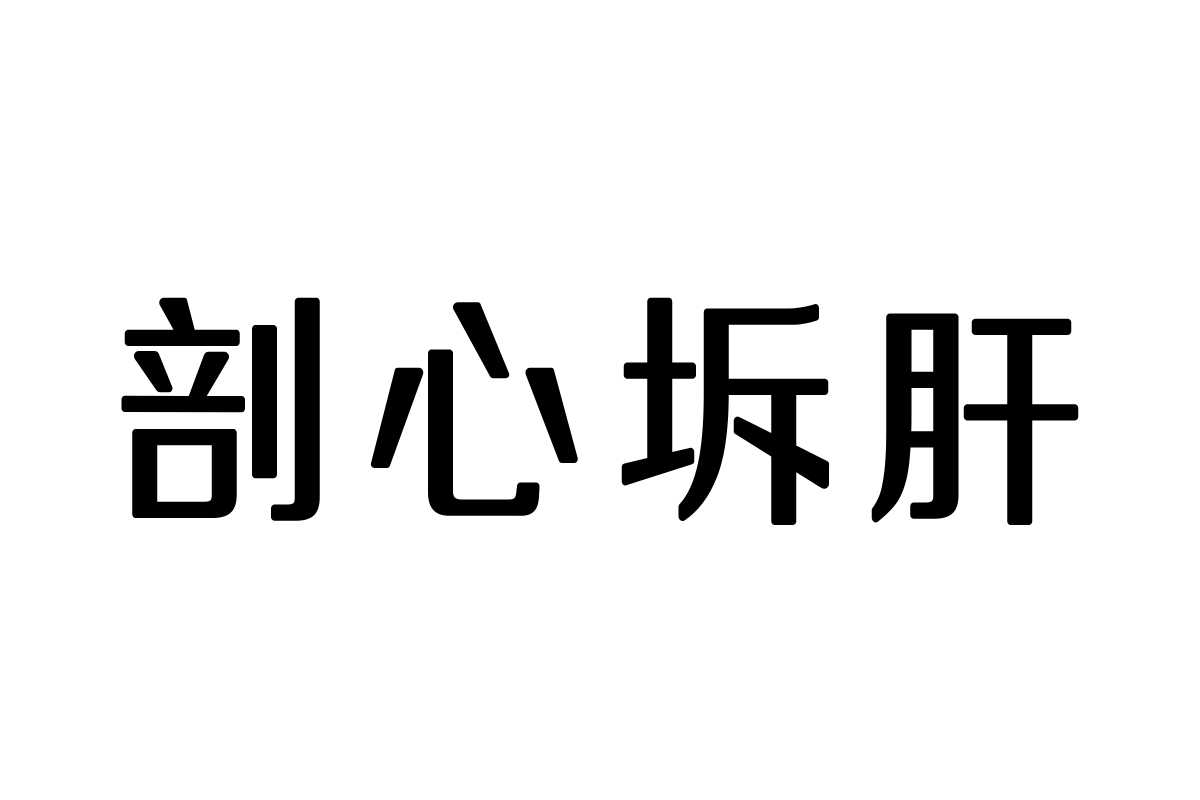
三极正典圆字体是一套中文字体,由北京华文在线科技有限公司开发。该字体具有独特的设计风格和特点,适用于各种应用场景。以下是对三极正典圆字体的一些介绍:
1. 设计风格:三极正典圆字体采用现代简约风格,线条流畅,字形圆润饱满,整体给人一种简洁、大气的感觉。
2. 字重选择:该字体提供了多种字重供用户选择,包括常规字重、粗体字重等,以满足不同场景的需求。
4. 应用场景:该字体适用于广告设计、网页设计、PPT演示、书籍排版等多种场景,能够满足不同用户的使用需求。